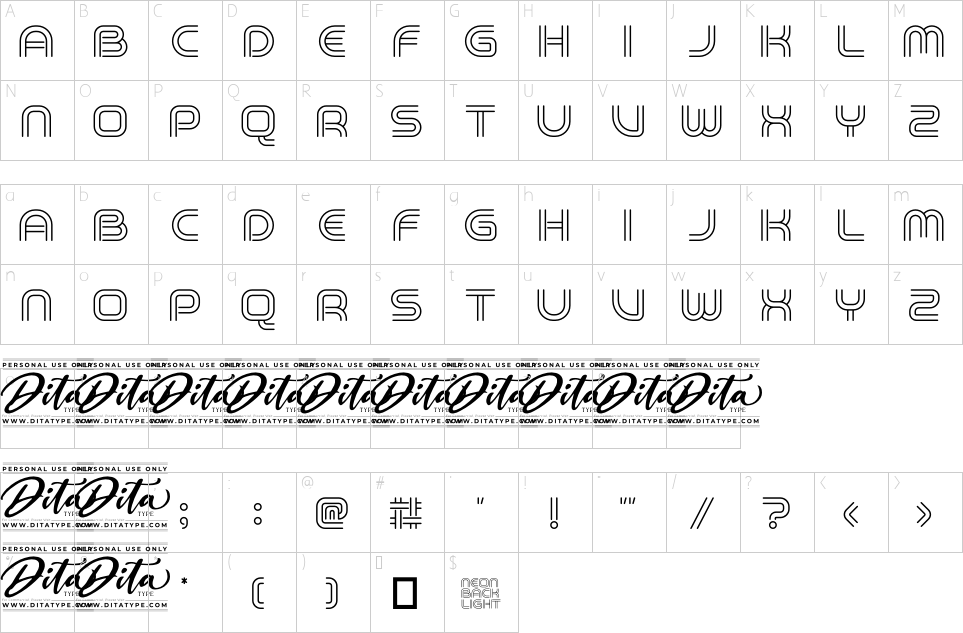
A Neon Backlight é uma linda fonte desenhada por Dita Type que destaca-se com suas formas curvas e detalhes vívidos, criando um efeito de iluminação noturna que se assemelha a luz neon. Suas linhas retas e luminosas dão ao texto uma sensação vibrante e ativa que pode ser ideal para aplicativos como letras de música ou design gráfico de interiores. Com este download da fonte gratuita para Windows e Mac, você adiciona um toque especial e único à sua criação. Recomendamos testar a Neon Backlight para experimentar seu impacto visual no texto.